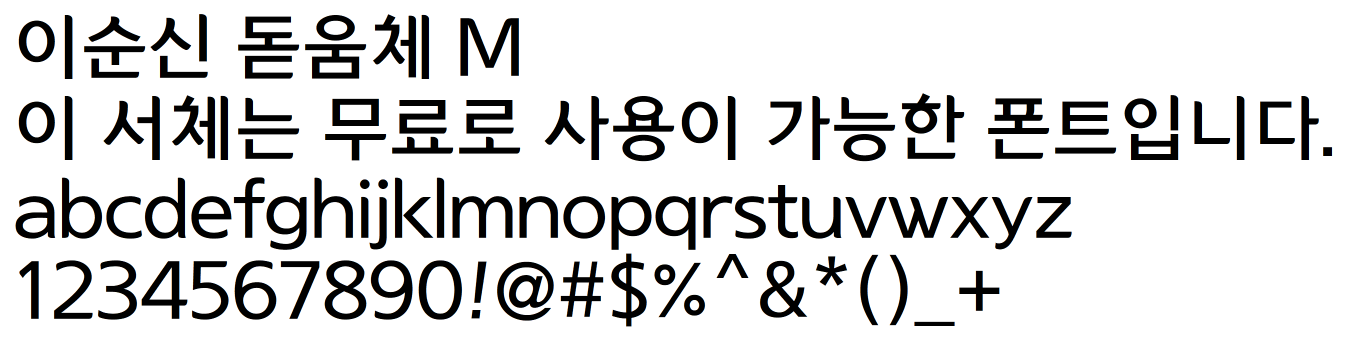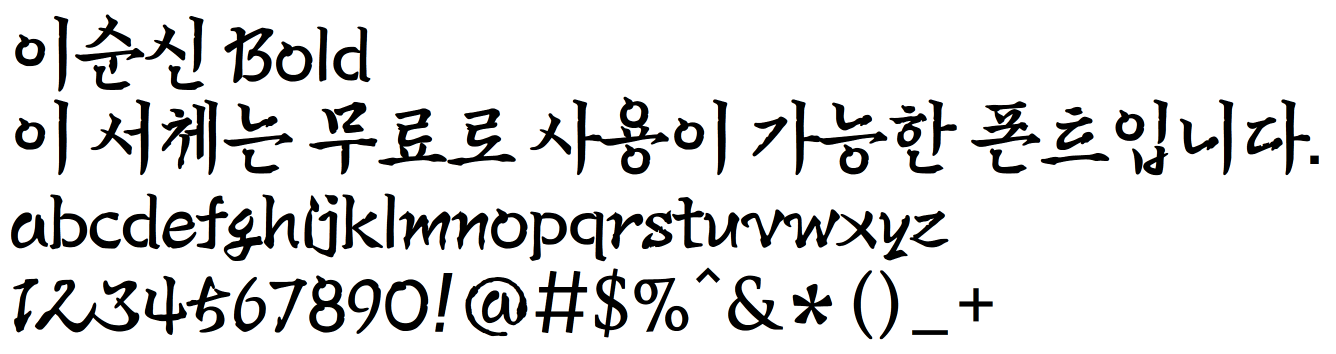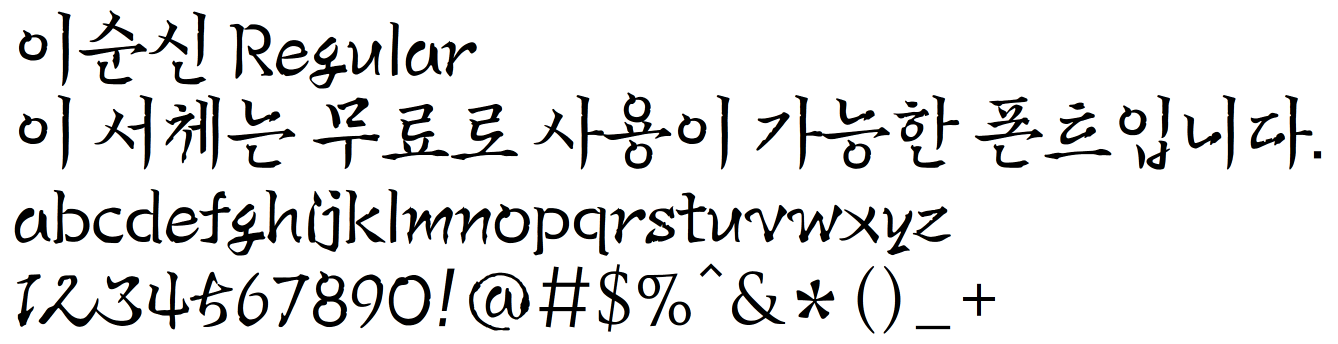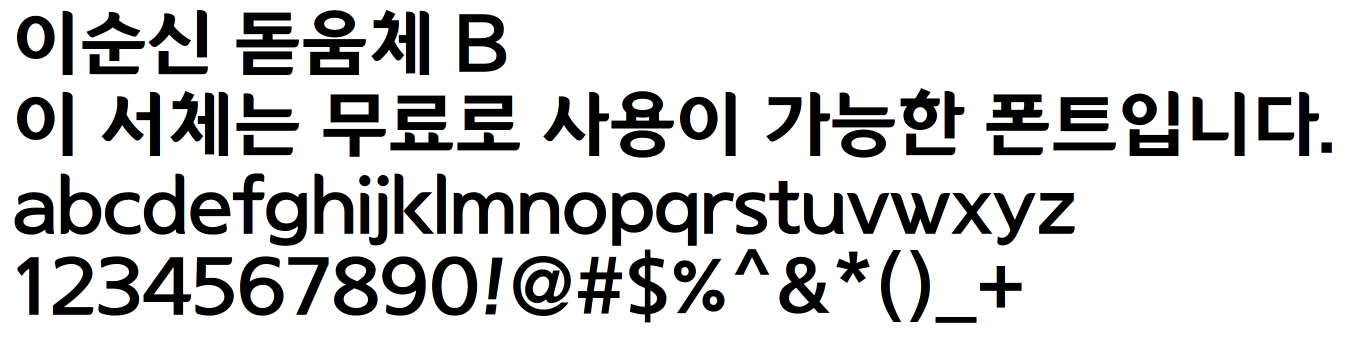
이순신체
이순신체 & 이순신 돋움체
아산시는 모두가 제약없이 아름다운 한글을 쓸 수 있도록 이순신체와 이순신돋움체를 만들어 무료로 배포하고 있습니다.
이순신 장군, 한번 더 세종대왕과 만나다!
작년 이순신 장군의 강인한 필체를 모티브로한 '이순신체' 를 선보인 아산시가 제570돌 한글날을 맞아 이순신 장군의 강직함, 정의로움, 곧은 정신과 함께 미래를 위해 나아가는 진취적이고 역동적인 아산시의 비전을 담은 '이순신 돋움체' 를 다시 한번 선보인다!
2016년 10월 9일 새롭게 선보이는 이순신 돋움체는 제570돌 한글날을 맞아 이순신 장군의 강직함, 정의로움, 곧은 정신과 함께 미래를 위해 나아가는 진취적이고 역동적인 아산시의 비전을 담았다.
'이순신체' 는 이순신장군께서 생전에 썼던 난중일기의 한문서체를 모티브로한 한글 디지털폰트로이순신 장군 한문서체의 주요특징을 유지하면서도 현대적인 개념을 접목시켜 이순신 장군의 강인함과리더십을 다시 한번 되새기고, 더불어 한글의 가치를 되새기는 계기가 되길 바라면서 개발된 서체이다.